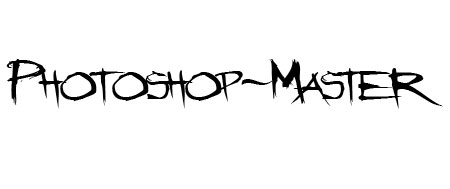
Великолепный Шрифт
Действительно жуткий шрифт!!! плюсом будет добавление эффекта растекания у буквам))
Просто отлично! *-*
Супер!!Мне такой очень нужен!
СУПЕР .. ТО ЧТО НУЖНО
интересный шрифт
немного смахивает на грайндкор:DD
СупеР)Давно искала такой шрифт)))
Интересный шрифт. спасибо